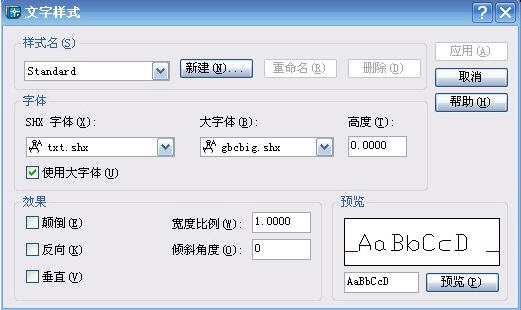
cad字體gbcbig.shx是autocad的一款大字體文件,字形偏大,筆畫(huà)細(xì)直,cad中使用挺多的,很多需要做圖紙的朋友可以使用這個(gè)字體,非常的不錯(cuò),需要的朋友,趕快來(lái)綠色資源網(wǎng)下載吧!
gbcbig.shx字體,這個(gè)字體是auto CAD軟件的大字體,在打開(kāi)CAD圖紙的時(shí)候,有時(shí)會(huì)提示需要這種gbcbig.shx字體的選擇,如果沒(méi)有這個(gè)gbcbig.shx大字體的支持,那打開(kāi)的DWG圖紙里的文字就會(huì)出現(xiàn)問(wèn)號(hào)。